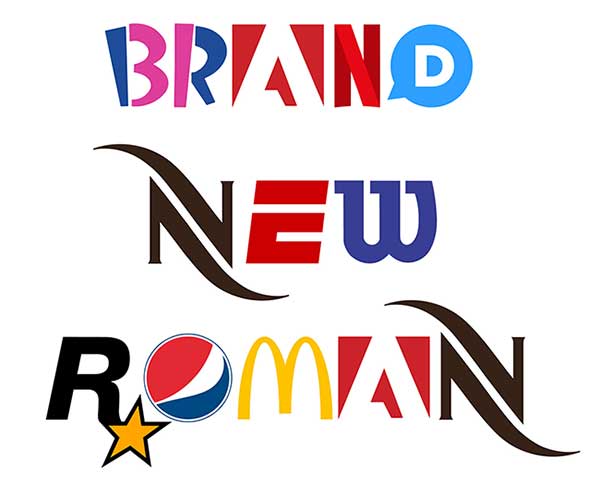
Les logos de marques sont partout, mais là où on s’attend le moins à les trouver c’est certainement dans un jeu de polices de caractères comme celui qui vient d’être mis en ligne par Hello Velocity.
Des textes qui ‘Marques’
Les créatifs de cette agence new-yorkaise ont en effet imaginé la plus originale et amusante série de fonts qui plaira autant aux fans des marques qu’aux amateurs de typographie…
Proposée gratuitement, cette police intitulée ‘Brand New Roman’ va vous permettre d’écrire tout ce que vous voulez avec son alphabet uniquement fait des iconiques logos de marques internationales ou tout du moins de leur typographie bien caractéristique. Si vous êtes sceptique sur le rendu final d’un texte ainsi composé, vous pouvez faire un essai directement sur le site dédié avant de récupérer la police en question que vous pourrez aussitôt utiliser sur votre Mac ou PC.